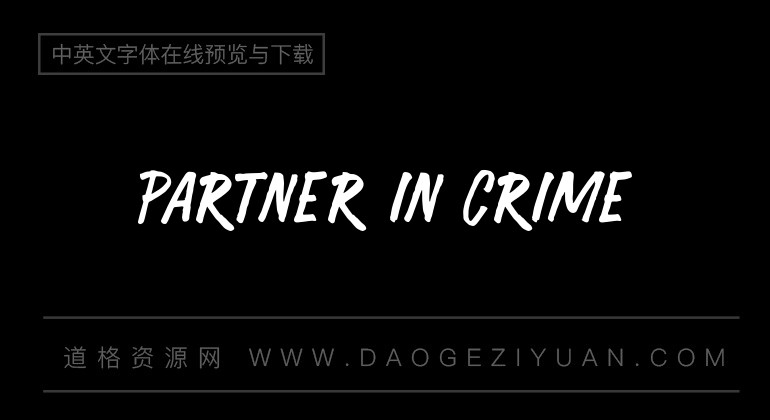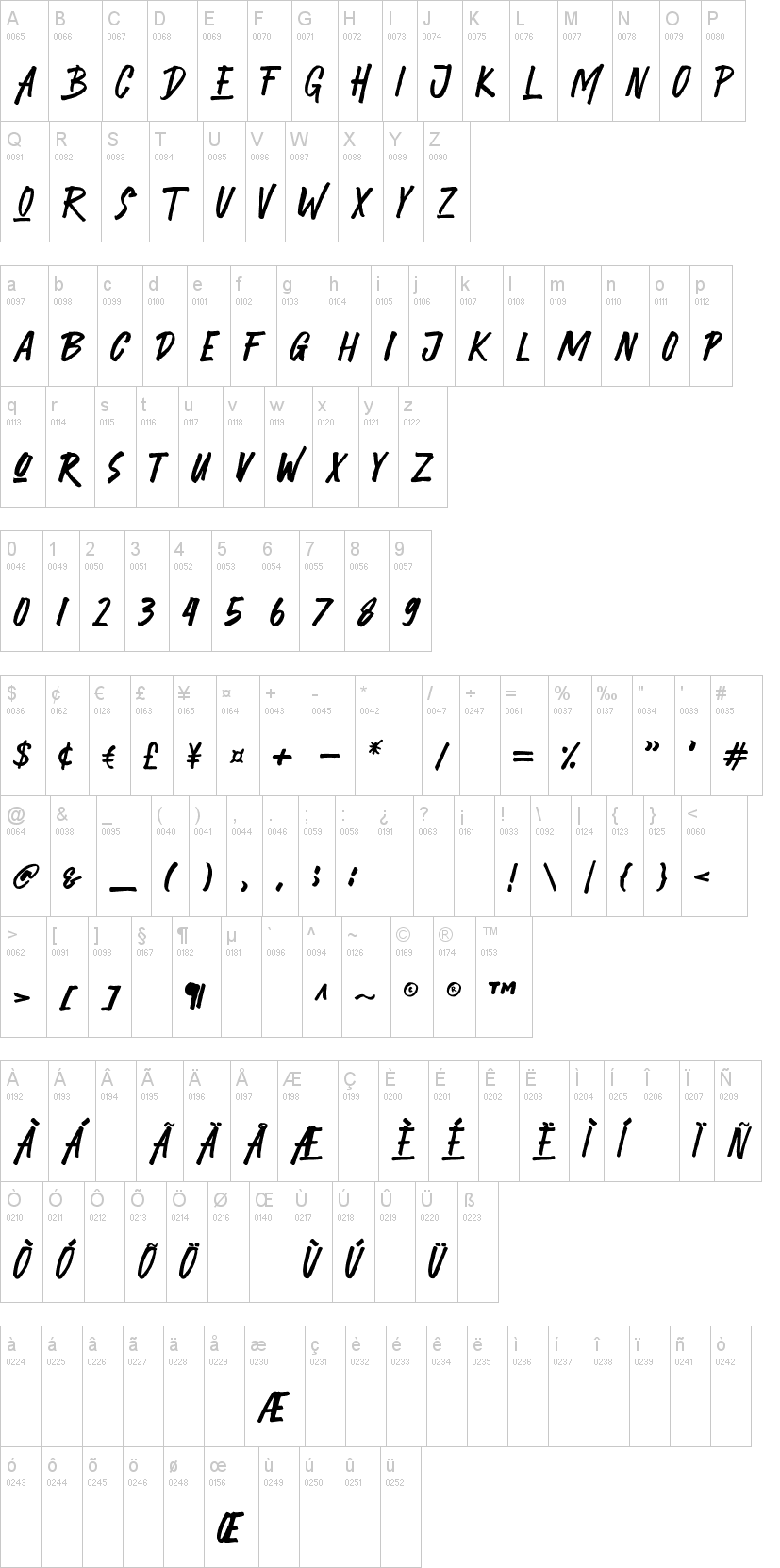
Partner in Crime 字体是一种免费的手写风格字体,由Kimberly Geswein设计并发布。该字体具有轻松、自然和友好的外观,它的笔画仿佛是手写的,因此非常适合用于各种项目的设计,尤其是卡片、海报、标志和包装设计。Partner in Crime字体包括大写字母、小写字母、数字和标点符号,支持英语、西班牙语、法语、德语、意大利语、葡萄牙语和斯堪的纳维亚语等多种语言,适用于Windows和Mac操作系统。内容介绍
Partner in Crime是一款非常不错的手写艺术字体,具有很好的视觉感,适合于文化类的宣传设计、商业类品牌的广告和产品包装设计以及个性化文字排版等较多场景。